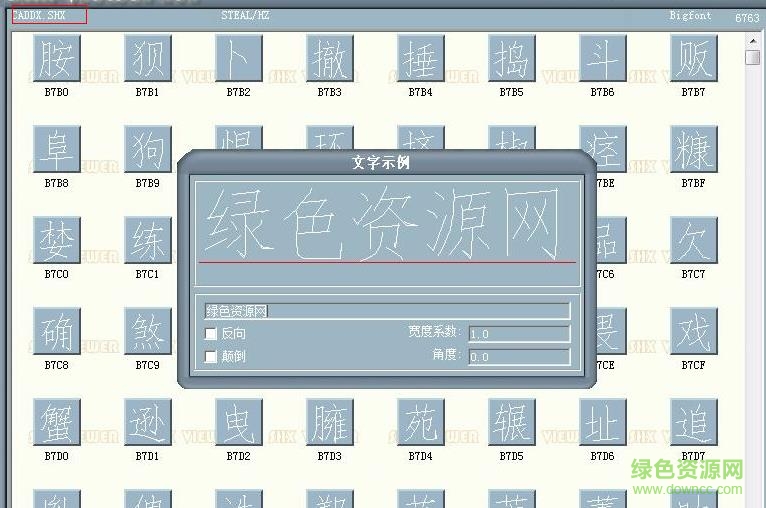
通過在這款字體中添加眾多設(shè)計(jì)元素,讓你能夠運(yùn)用到眾多的工業(yè)設(shè)計(jì)當(dāng)中以及矢量圖設(shè)計(jì)當(dāng)中,其內(nèi)的線條搭建出的字體十分獨(dú)特!
1.十分的美觀,在設(shè)計(jì)過程中廣受設(shè)計(jì)師喜愛
2.表現(xiàn)形式十分獨(dú)特
3.能夠帶給你獨(dú)家的欣賞體驗(yàn)